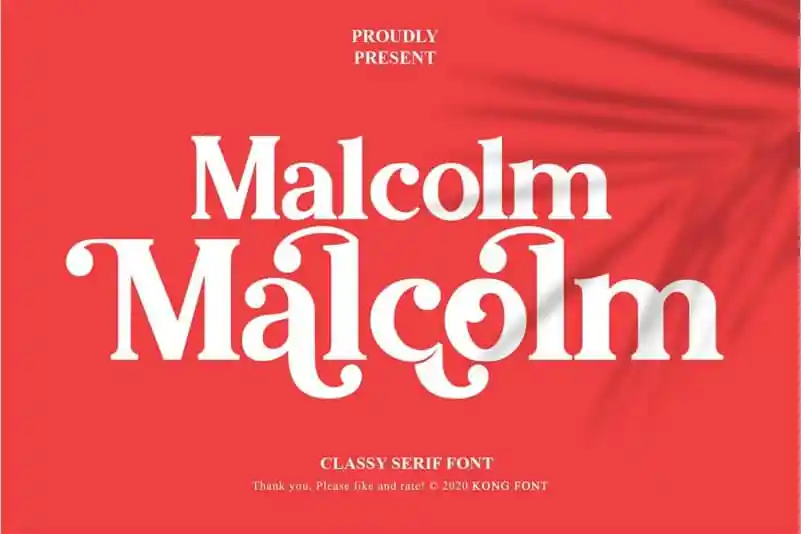
Malcolm Serif Font – Fonte Grátis
Malcolm Serif Font
Olá, amigos. Estou aqui uma fonte serif clássica e moderna chamada Malcolm Serif Font. Ela é perfeita para quem busca tanto beleza clássica quanto um toque de modernidade no design. Com uma grande quantidade de ligaturas belas e sofisticadas que vão dar o toque final ao seu trabalho, ela tornará suas criações ainda mais impressionantes. Além disso, Malcolm Serif Font contém estrelas elegantes que irão adicionar um brilho especial a qualquer projeto. Este tipo de fonte é perfeito para criar logos, papéis de parede, eventos de casamento, convites, citações, redes sociais e sites, entre outros muitos usos. Adorei saber que você está procurando por uma fonte tão versátil como o Malcolm Serif Font. Que tal adicionar esse toque final a seu próximo projeto?